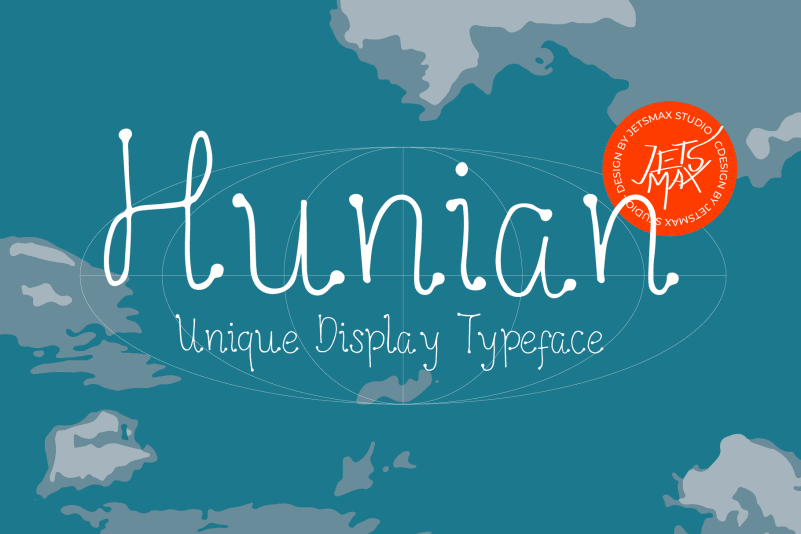
Hunian Display Font – Download Grátis
A Hunian Display Font é uma tipografia de destaque criada a partir de traços desenhados à mão que se curvam em maneiras únicas e especiais, adequadas para complementar seus projetos criativos. Esta fonte exibe um carácter elegante e contínuo, com formas arredondadas e curvas suaves que permitem uma leitura fluida mesmo em espaçamentos reduzidos. Ideal para estilos de design moderno ou vintage, a Hunian Display se presta perfeitamente para banners publicitários, selos de marca, letras gigantes nos anúncios, elementos gráficos de revistas e jornais, e até mesmo para artesanato personalizado. Seja você um designer de moda, arquiteto ou freelancer de marketing digital, esta fonte pode enriquecer seu trabalho com uma aparência única e sofisticada.